Points forts de la fonderie Mark Simonson.
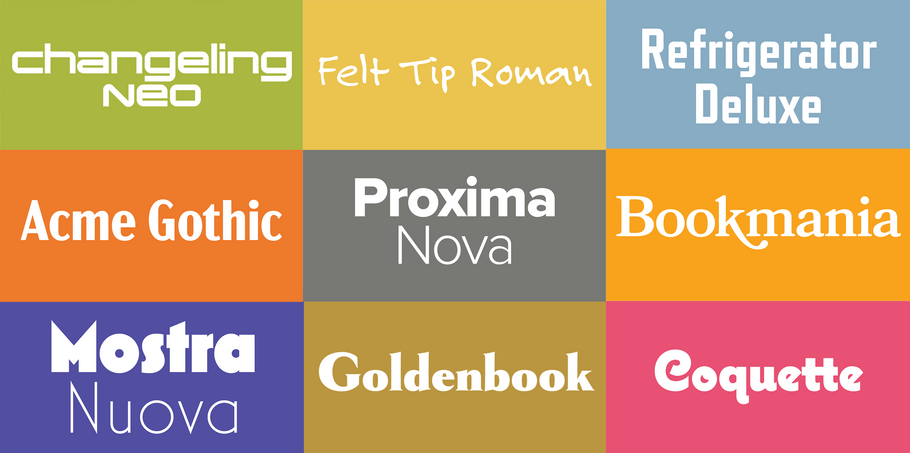
Mark Simonson.
Mark Simonson s’est intéressé très tôt aux lettres et a développé une passion pour l’art, ce qui l’a amené à débuter sa carrière sous la double casquette de directeur artistique de magazine et de designer graphique. Pendant des années, Mark a ébauché des polices de caractères à ses heures perdues avant de publier sa première police, Felt Tip Roman, en 1992. Toutefois, il ne s’est pas consacré à plein temps à cette activité avant l’an 2000, date à laquelle il a créé le Studio Mark Simonson à St. Paul, dans le Minnesota. Depuis, cette entreprise individuelle connaît un grand succès avec des polices très populaires comme Mostra Nuova, Coquette et surtout Proxima Nova, utilisée dans des milliers de sites web à travers le monde.
Proxima Nova
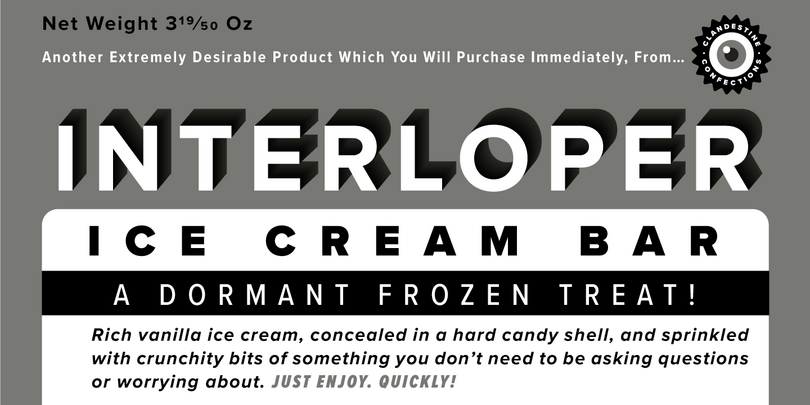
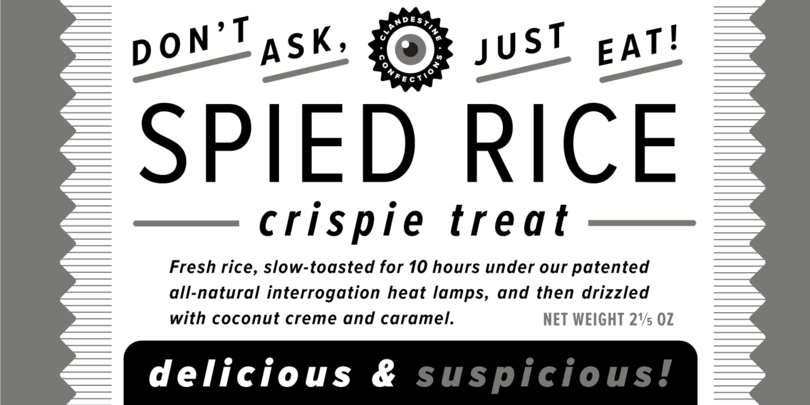
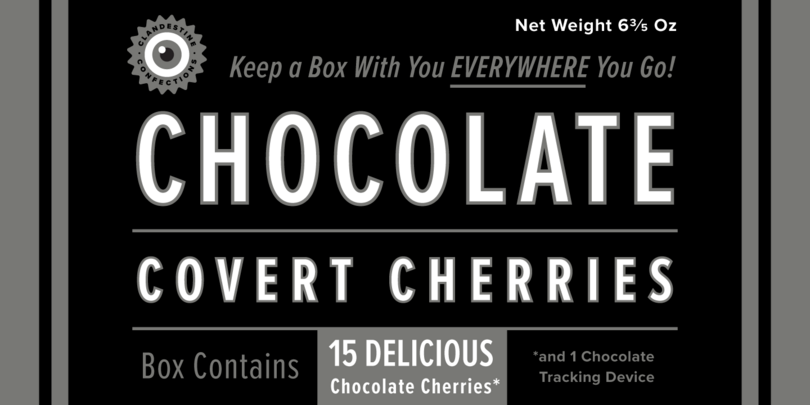
La famille Proxima Nova est une refonte complète du type Proxima Sans (1994). Les six polices originales (trois graisses et leur version italique) ont été enrichies pour constituer une famille de 48 polices OpenType riche en fonctionnalités. Elle est disponible en trois largeurs : Proxima Nova, Proxima Nova Condensed et Proxima Nova Extra Condensed. Chaque largeur comprend 16 polices, soit sept graisses et les italiques correspondantes. Du point de vue stylistique, Proxima Nova comble l’écart entre des polices telles que Futura et les types classiques sans empattement. Il en résulte un type hybride alliant des proportions modernes et humanistes à un aspect assez géométrique. Proxima Nova figure parmi les 50 polices les plus vendues sur MyFonts. C’est une police utilisée dans des milliers de sites web à travers le monde.
Felt Tip Roman
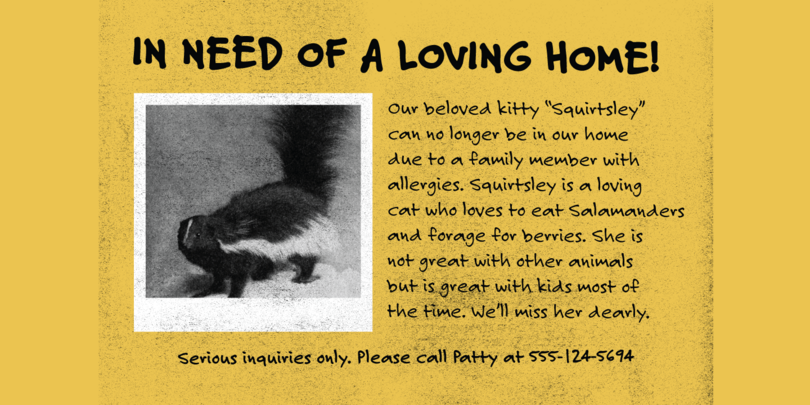
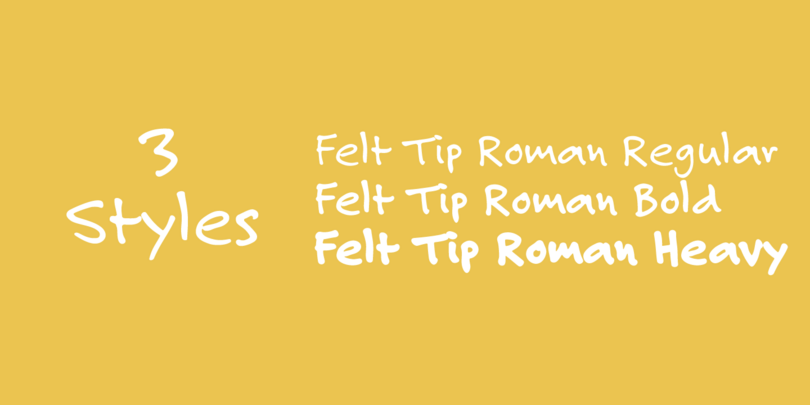
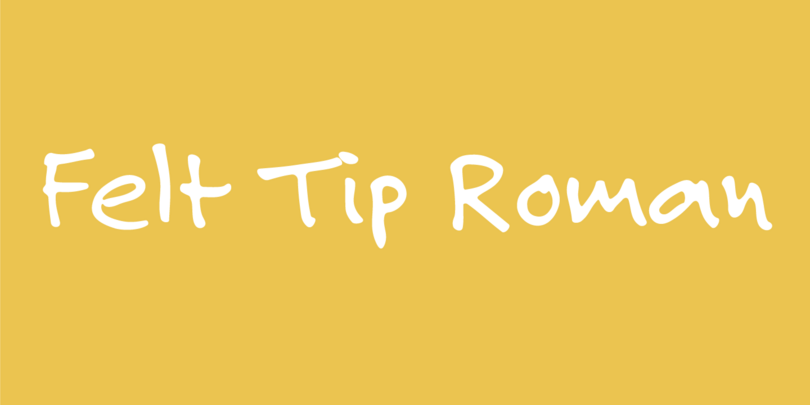
Felt Tip Roman, première police publiée par le designer, a été créée en 1989 à titre d’expérience. Elle est ensuite devenue l’une de ses polices les plus populaires. Il s’agit d’une adaptation directe de son écriture manuscrite, qui a été étendue en 2003 pour inclure les graisses Bold et Heavy afin d’élargir son champ d’utilisation.
Mostra Nuova
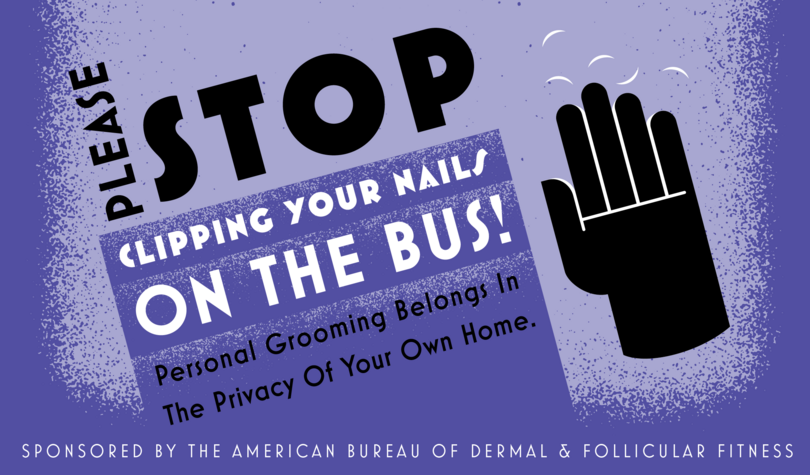
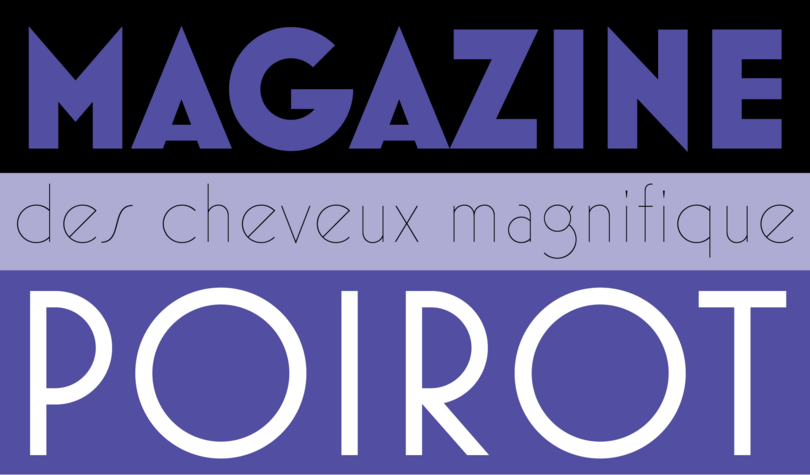
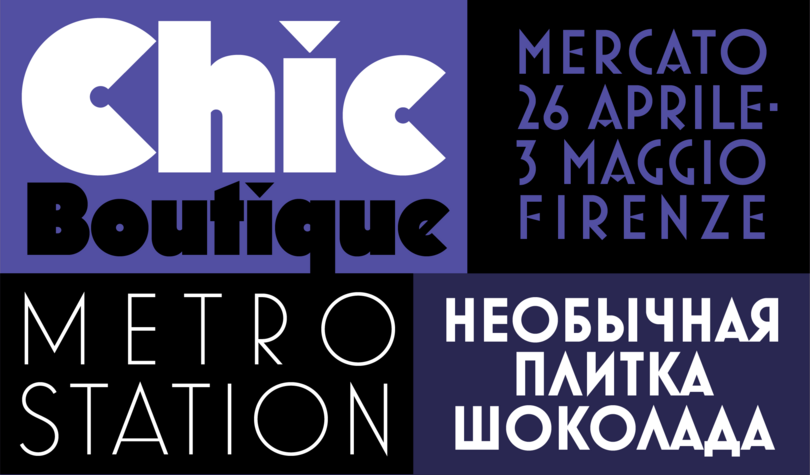
Mostra Nuova est une police basée sur un style de lettrage souvent utilisé dans les posters Art déco italiens et les publicités des années 1930. Cette police géométrique joue sur de subtils ajustements optiques qui lui confèrent un aspect plus doux. Mostra Nuova contient de nombreux caractères alternatifs qui représentent les variations typiques du lettrage Art déco italien. Elle peut être utilisée dans d’innombrables combinaisons afin de capturer une atmosphère ou un style particulier. Cette famille comprend neuf graisses et offre un jeu étendu de caractères latins (la plupart des langues latines d’Europe de l’Ouest et de l’Est sont prises en charge) ainsi qu’un jeu de caractères cyrilliques (y compris des variantes locales pour le bulgare, le serbe et le macédonien).
Goldenbook
Goldenbook est basé sur le logotype d’un magazine littéraire de la fin des années 1920, intitulé The Golden Book Magazine. Avec sa touche Art déco sur les formes de lettres latines classiques, cette police bas-de-casse est destinée à un usage dans les grandes tailles. On la retrouve souvent sur les couvertures de livres. Goldenbook comprend des chiffres elzéviriens et linéaires dans chaque graisse et prend en charge le cyrillique, ainsi que d’autres fonctionnalités typographiques intéressantes telles qu’une esperluette alternative et un R majuscule à long jambage.
Coquette
Coquette est une police cursive verticale combinant des éléments d’écriture traditionnelle de la langue française et des styles géométriques sans serif. Résultat : une police à la fois innovante et familière, évoquant le lettrage vernaculaire et commercial du milieu du XXe siècle sans qu’elle soit dérivée d’une source existante spécifique. Initialement publiée en 2001 avec trois styles ((Light, Regular et Bold), cette famille de polices a été mise à jour en 2017 et comporte désormais trois nouveaux styles (Thin, ExtraBold et Black) et diverses nouvelles fonctionnalités, notamment des caractères alternatifs, des fractions OpenType, des exposants, des ligatures en f et des caractères mathématiques. Coquette est adopté pour un large éventail d’applications, par exemple les emballages, les présentations en magasin et les couvertures de livres.
Refrigerator Deluxe
Refrigerator Deluxe est une version étendue et enrichie de Refrigerator, un type géométrique, sans serif et condensé inspiré par le lettrage générique par blocs typiques du milieu du XXe siècle et souvent utilisé dans les manuels de lettrage. Refrigerator Deluxe présente de nombreux caractères alternatifs pouvant servir à créer toutes sortes de variations, allant de la « lettre de bloc » basique à l’élégant style Art déco, grâce à la magie d’OpenType. Refrigerator Deluxe est une police parfaite pour évoquer l’époque qui produisait d’énormes réfrigérateurs bourdonnants, mais elle convient aussi pour mettre en valeur la couverture de livres sur la politique contemporaine ou la culture urbaine.
Changeling Neo
Changeling Neo est une version étendue et enrichie de la police Changeling (2003), elle-même étant une refonte et une extension de China, une police de Visual Graphics Corporation du milieu des années 70 conçue par M. Mitchell. Changeling Neo comporte plus de graisses et de styles que la famille d’origine, des caractères revisités pour un rendu plus affirmé ainsi qu’un jeu complet de variantes bas-de-casse, offrant des combinaisons « unicase » infinies.
Acme Gothic
Acme Gothic (2018) est basé sur les pleins et les déliés des lettres gothiques, style populaire aux États-Unis dans la première moitié du XXe siècle. Des polices de ce genre ont déjà existé, mais elles étaient trop originales (Globe Gothic), trop britanniques (Britannic), trop Art déco (Koloss), trop modernes (Radiant) ou trop Art nouveau (Panache). Aucune ne saisit le style simple, trivial et vernaculaire d’Acme Gothic. Cette famille de polices offre 25 styles différents et prend en charge un grand nombre de langues couvrant la plupart des systèmes d’écriture latins. Acme Gothic inclut également des petites capitales en exposants (accessibles via un jeu stylistique OpenType). On trouve ces deux variantes dans des exemples vintage de ce style de lettrage.
Grad
Phil Martin, créateur de plus de 400 polices entre la fin des années 60 et les années 80, a conçu Grad au début des années 90 comme une refonte de la police classique Century Schoolbook, pour son usage personnel à l’origine. En modifiant les polices au format bitmap sur PC DOS, il a apporté bon nombre de modifications au design, subtiles ou plus visibles selon les cas, et a ajouté de nouvelles fonctionnalités, notamment des petites capitales, des chiffres elzéviriens, des ligatures et des capitales ornées. Cependant, Grad est resté bloqué pendant dix ans sur l’ancien ordinateur DOS de Phil dans un format obsolète. À partir d’impressions laser fournies par Phil et de spécimens de la police d’origine Century Schoolbook de ATF, Mark Simonson a mis cette police au goût du jour en créant une famille de trois polices OpenType offrant un foisonnement de fonctionnalités.
Bookmania
Bookmania (2011) combine l’élégance robuste de la police originale Bookman Oldstyle (1901) avec l’exubérance ornementale des polices Bookman des années 60, mais y ajoute toutes les fonctionnalités que l’on attend d’une famille de polices numérique moderne. Avec plus de 680 caractères ornés, soit plus que toute autre police Bookman précédente, les possibilités sont infinies. La large gamme de graisses en fait une police de titrage parfaite, mais également adaptée au texte. Contrairement à certaines réinterprétations du type Bookman, la version italique conserve l’axe incliné purement latin.